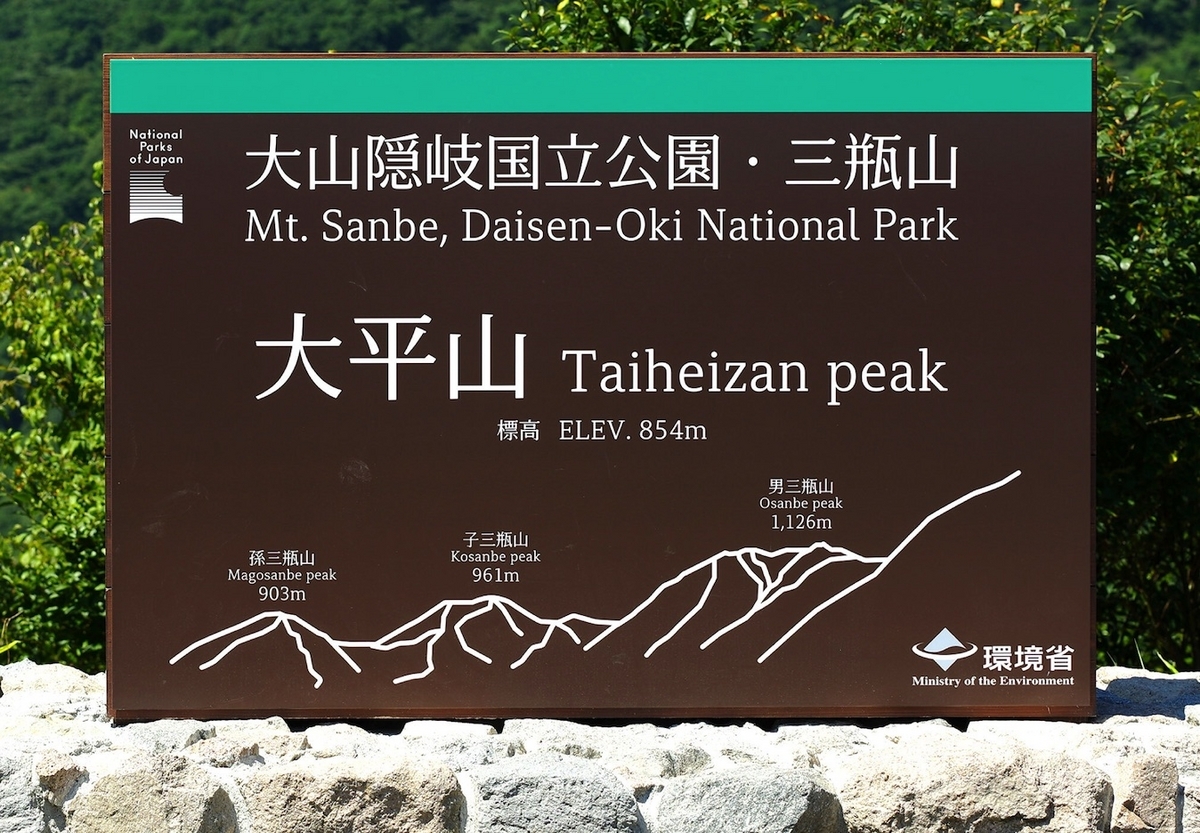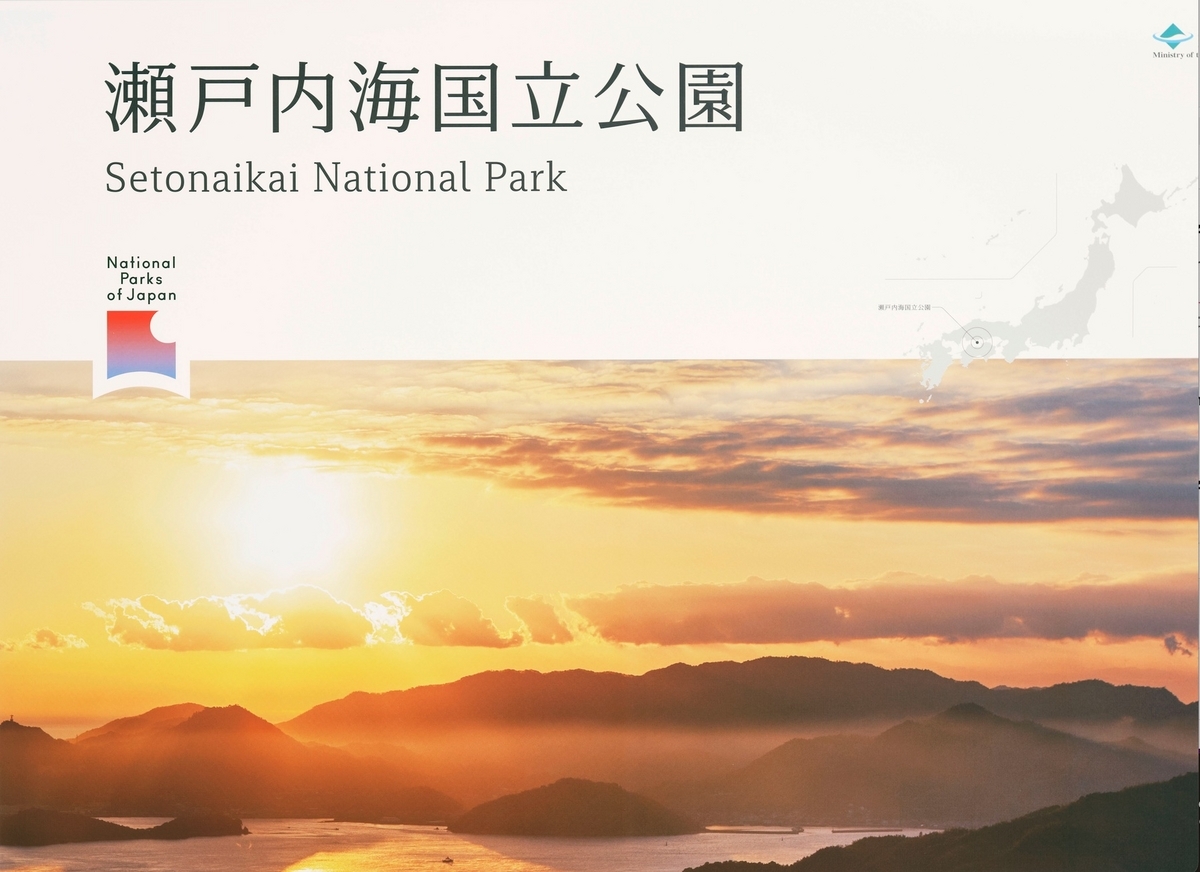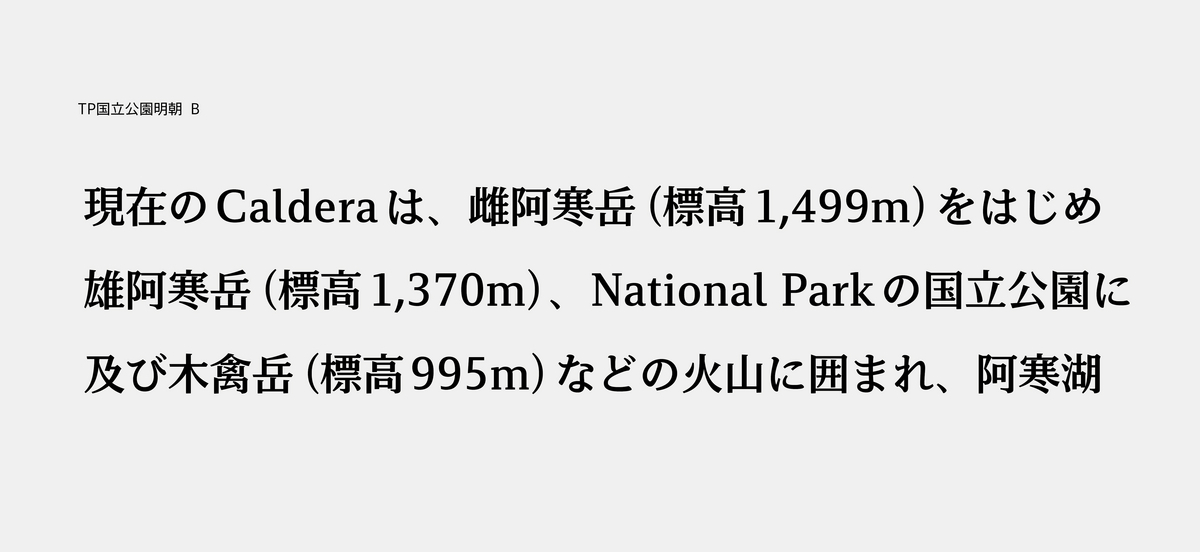
タイププロジェクトが国立公園用専用フォント「TP国立公園明朝 Bold」の提供を開始。環境省の国立公園オフィシャルパートナーや国立公園事業者でも使用を開始
タイププロジェクトは、環境省向けに、オリジナルデザインの欧文書体とTP明朝を組合せた国立公園専用フォント「TP国立公園明朝 Bold(ボールド)」を提供したことを2024年4月25日に発表した。
TP国立公園明朝は、環境省により2016年にスタートした「国立公園満喫プロジェクト」の一環として開発が始まった。
2019年には、TP国立公園明朝 Regular (レギュラー)とLight (ライト)を提供し、全国の国立公園の公共標識やリーフレットで広く使われている。
国立公園専用フォントとしてTP国立公園明朝の使用を開始して数年が経ち、解説板や標識等において、距離が離れていても読みやすく視認性が高い書体、また、希少な野生動植物の保全のための啓発内容等の重要な情報を強調して表現するためのより太い書体の必要性が高まっていた。
タイププロジェクトでは、RegularやLightウエイトの開発時と同様に、国立公園のブランディングを担当した日本デザインセンターのアートディレクターである色部義昭氏と協議を重ね、新たにBoldウエイトを開発。
Boldウエイトは、「国立公園の澄み切った空気のような世界観をキープ」することをコンセプトに、誘目性よりも可読性を優先し、遠くからでも読みやすいように調整している。
タイププロジェクトの代表取締役である鈴木 功氏は、「TP国立公園明朝は、明朝体のもつ情緒性と雨風に耐えうる堅牢性を兼ね備えた書体です。今回Boldウエイトが加わったことで、遠距離からの視認性がさらに向上しました。TP国立公園明朝が、国立公園を訪れた人たちの案内役として役に立つことを願っています」と述べている。
環境省 国立公園課 国立公園利用推進室では、「日本の国立公園の価値や魅力についての認識の浸透・定着を図り、国立公園のブランディングを推進するために、より視認性の高いBoldウエイトが追加できたこと、また多様なパートナーと連携して国立公園のブランディングに取り組めることを喜ばしく思っています」と述べている。